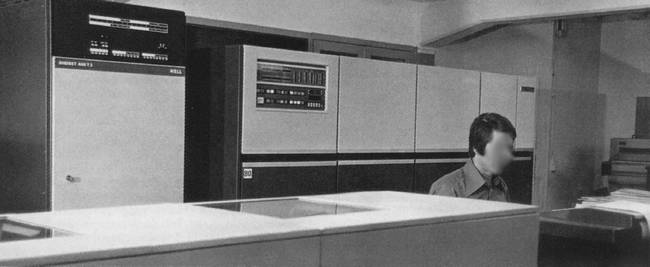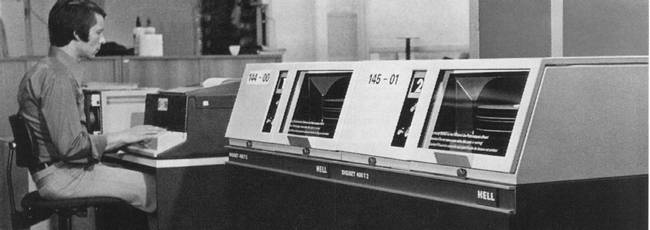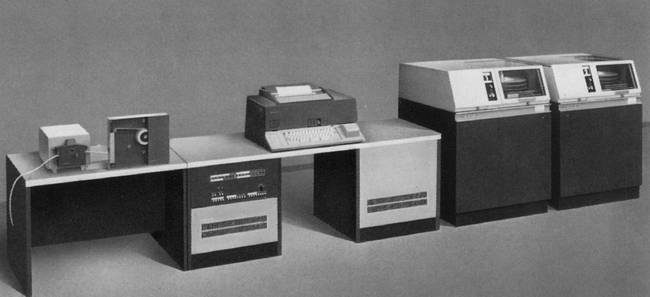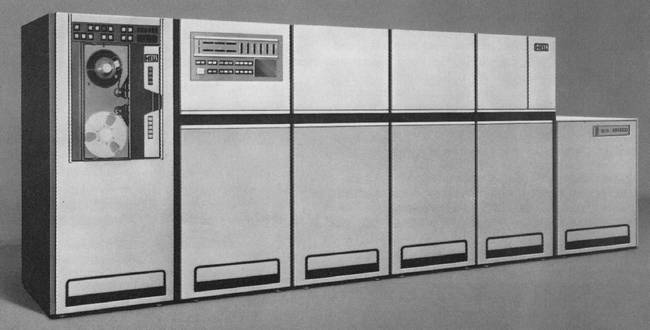
Kleine Umfrage: typografische Meilensteine?
Eine der ersten hier gekauften war jene:
Sonst war Helvetica zu 90 % die erste Wahl, weil sie eben durch den Laserdrucker verfügbar war.
Ich frage mich warum immer wieder die Baskerville aufkommt wenn es um die ‘Barock-Antiqua’ geht. Baskerville war einer der Ersten der die Antiqua-Alphabete der die mit der Spitzfeder schreibenden Kalligrafen wie Joseph Champion (siehe George Bickham’s Universal Penman) von einige Jahrzehnte zuvor als Bleisatzschrift umsetzte. Baskerville war demnach, zumindest im Bereich der Stempelschneider, ein Neuerer und keine Übergangsfigur. Es sind eher Caslon und Zeitgenossen die zwar gewisse Eigenheiten der Spitzfederschrift (z.B. der Kuller am Ende der a-, f- und r-Bögen) in ihre Schriften einfließen ließen, aber was der Art des Strichstärkenkontrast beim bis dahin traditionellen Modell blieben. Daher die ‘heimlich’ schräg gestellte Achse der Rundung im ‘o’ der Barock-Antiqua und die relativ kräftige horizontale Bögen in h, m, n und u. Diese kommen bei Baskerville nicht mehr vor.
Um aus den ‘digitalen Schneider’ herauszukommen, möchte ich vorschlagen, dass du den Begriff ‘digitale Schrift’ zuerst (für dich) definierst. Dass damals die ersten digitalen Schriften auf teuren Maschinen liefen, war für Grafik-Designer kein Kriterium diese zu verwenden oder nicht. Auch die Bleisatz- und Fotosatzmaschinen waren teuer. Diese waren aber alle ‘zugänglich’ für normalsterbliche Grafikdesigner. Seit der Entstehung unseres Berufes in den 1920er Jahre hat man als Grafik-Designer den Satz inklusive der Schriftwahl spezifiziert und hat damit eine Setzerei beauftragt. Grafik-Designer oder Agenturen die ihre eigene In-House Setzerei hatten waren absolute Ausnahmen. Das ging erst Ansatzweise mit dem Fotosatz (Diatype); wer trägt schon die Bleisatzseiten in eine Druckerei an einem anderen Ort? Als Grafik-Designer hat man in der Regel mit den Satzfahnen das Layout geklebt (Papier auf Fotokarton), was dann nach Freigabe idealerweise in die Filmmontage reingezeichnet wurde. Es war der Kunde der, neben dem Entwurf, den Satz, die Reinzeichnung und den Druck bezahlt hat. Also so wie es heute immer noch ist. Es hat sich mit der Einführung des DTP nur die Arbeit von der Setzerei und der Reinzeichnung (Litho) zum Grafik-Designer bzw. in die Agenturen verlagert. Die Verfügbarkeit bestimmter Schriften war bis dahin eher ein Problem der Setzereien, weil jedes Satzsystem eine eigene herstellerspezifische Schriftbibliothek hatte. Auf der Monophoto hat es beispielsweise die Frutiger nie gegeben … Am Anfang (sagen wir mal 1989) war DTP gar nicht billig. Da hat ‘Gutenberger’ recht: Ein Apple Macintosh IIfx mit 19" Graustufen-Monitor kostete damals so an die 24.000 D-Mark und dann kamen noch der Apple Laserwriter NTX und die Software dazu. Unter 30.000 D-Mark war also nichts mit DTP und drei Jahre später war dann alles restlos veraltet. Ganz schön happig, wenn man das vergleicht mit der Investition einer Schneidematte, ein Zeichentisch, ein Leuchttisch und vielleicht sogar eine Repro-Kamera. Die hatten bis dahin eine ganze Karriere lang gehalten … Es spricht von selbst, dass es einige KollegInnen gab, die den Sprung zum DTP nie geschafft haben, oder bei der zwingende Anschaffung eines neuen Rechners ihren Beruf aufgeben mussten.
Mein Vorschlag: Digital ist digital. Also Hell, Linotronic oder Compugraphic. DTP ist die nächste Stufe gewesen.
Lars hat vermutlich recht, wenn er sagt, dass die Digi Grotesk S die erste digitale Satzschrift war. Wobei ‘S’ (laut G. G. Lange) für Siemens stand, weil die Firma Siemens damals die Neuzeit Grotesk als Hausschrift definiert hatte und diese von Stempel hinsichtlich einiger Schriftzeichen hat überarbeiten lassen. Die Neuzeit-Grotesk S (und somit auch die Digi-Grotesk S) ist also keine Helvetica-Clone, aber eher eine in Richtung der Helvetica ‘modernisierte’ Neuzeit Grotesk.
Die Antworten von Lars und Ralf haben mir die Frage in dem Sinne beantwortet, in dem ich gefragt hatte. Damit habe ich zum einen die wirklich erste Schrift, die digital gesetzt wurde, zum anderen die ersten Schriften, mit denen Setzer und Gestalter dann an Rechnern zu arbeiten begannen (die sich also auch bei den Anwendern/Lesern in der Folge  etablierten). Für meine Fragestellung ist es dabei wirklich nicht wichtig, wie teuer das Ganze war. Mir geht es eher um das Verständnis dafür, wie die Geschichte der Druckschriften angefangen hat und welche Schriften damit als Meilensteine verknüpft sind.  :-)
Alle Informationen in diesem Strang sind wirklich hilfreich. Ich will keine wissenschaftlich Abhandlung verfassen, sondern eher in groben Zügen die Entwicklung der Druckschriften darstellen - eben unter Nennung der Schrift-Meilensteine. Schriften, die eine Neuerung in der Geschichte waren und eine gestalterische oder technische Zäsur darstellten, die die weitere Schriftentwicklung maßgeblich mit beeinflussten.
Könnt Ihr mir etwas dazu sagen, ob Frutigers Apollo wirklich die erste Fotosatzschrift war? Ich habe das noch nirgends bestätigt gefunden.
Fakt ist, dass Frutigers Apollo die erste Schrift ist, die Monotype für die Fotosetzmaschine Monophoto entwerfen ließ. Ob es auch die erste Fotosatzschrift ist, darf angezweifelt werden. Wenn ich mich recht entsinne, hatte man bereits in den 1920er Jahren Fotosetzmaschinen entwickelt – wie die Uhertype, für die u. a. Tschichold einige Schriften entwarf.
Ich finde ja, die Univers (bzw. Frutiger an sich) ist kein unbedeutender Meilenstein ... der erste(?) der systematisch Schriftfamilien aufgebaut hat.
Oder wäre es eine Corporate ASE, wo das Systematische dann auf ganze Sippen übertragen wurde?
(Bei beiden wäre aber zu klären, ob es wirklich die ersten ihrer Art waren.)
Ich finde das auch interessant: Welche Schriften waren in welcher Hinsicht die ersten ihrer Art? Es wäre spannend, das noch weiterzuführen: Die erste MM-Schrift, die erste Hybridschrift (Rotis?), die erste ttf/PS/OTF-Schrift, …
Wenn wir das jetzt hier noch so richtig ausspinnen, dann wäre die Frage, ob man das in irgendeiner Form aufbereitet für das Wiki gebrauchen könnte? Wäre ja schade, wenn all die Erkenntnisse einfach nur in die Tiefen des Archivs wandern …
Aber ob es der erste war?
Das war natürlich ein echter Bolide und weltweit das erste elektronische Satzsystem, das im Zeritungssatz gegen die Linotype-Zeilengussmaschinen Bestand hatte. Eine Glaslinse von ca. 30 cm Ø, die auf hochglanzverchromten, armdicken Stahlrohren an die Belichtungsebene herangeführt wurde, war im Inneren des Gerätes ebenso faszinierend wie die Kathodenstrahlröhre selbst.